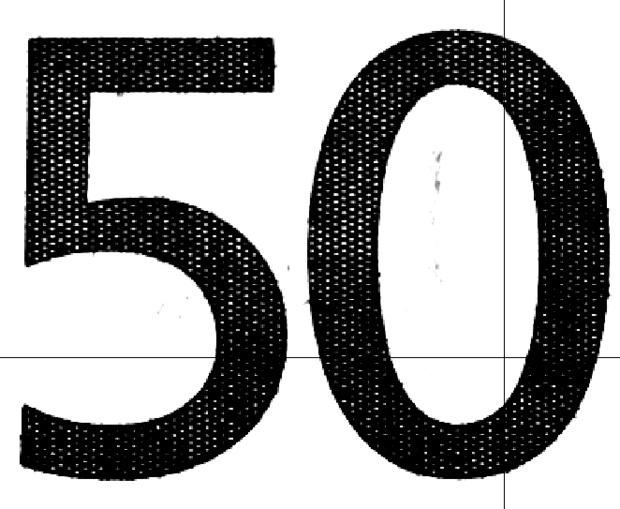
Euroschein-Schriftart
Frutiger Roman, würde ich sagen.
Frutiger Roman - warum bin ich da nicht drauf gekommen? hat mir doch whatthefont auch gesagt.
ich suche die typo links unten "euro" + "eurΩ" das ist eine helvetica black std wenn mich nicht alles täuscht oder?
und die "50" links oben ist das eine auf der y-achse skalierte Frutiger Roman? wer macht denn sowas bitte?
Das ist immer noch die Frutiger, diesmal die Black. :-)
Und die "skalierte Frutiger Roman" ist eine Frutiger Condensed :-)